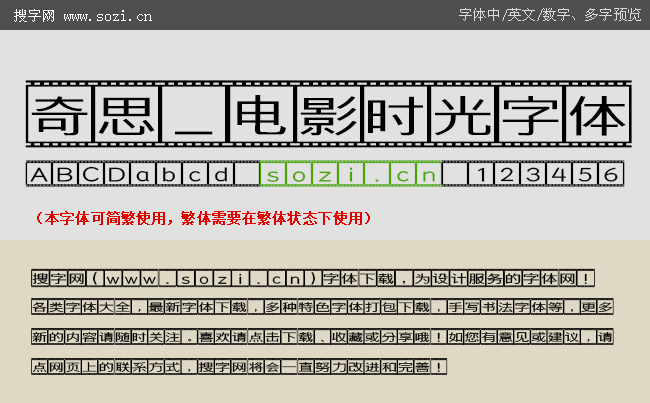
奇思_電影時光字體
搜字網(wǎng)提供一款奇思_電影時光字體手機(jī)中文藝術(shù)字體下載,奇思_電影時光字體是一款以黑體字為原形,為字體加上了電影膠片的圖案裝飾,適合在正式的場合來進(jìn)行使用,適合應(yīng)用于廣告設(shè)計、名片設(shè)計、包裝印刷、產(chǎn)品設(shè)計等應(yīng)用。